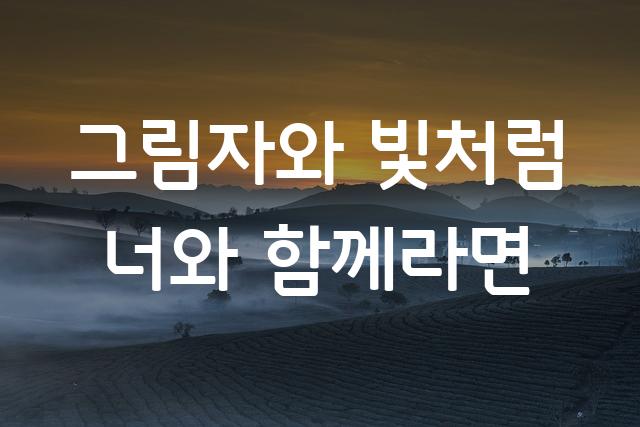
godo rounded는 NHN Commerce에서 제작한 폰트로, 그 이름처럼 동글동글한 영문 글꼴 특징을 가지고 있습니다. 이 폰트는 부드러운 곡선과 함께 친근하고 따뜻한 느낌을 전달합니다.
godo rounded은(는)
둥근 스타일, 감성적인, 자연감성, 부드러움, 복실복실 계열의 생김새를 가지고 있으며
로고 디자인, 광고 캠페인, 브랜딩 등에서 자주 활용되며, 효과적인 메시지 전달에 적합합니다.
이 폰트는 크리에이티브, 패션/뷰티, 건축/인테리어 분야에 잘 어울리며,
세련된, 창의적인, 고급스러운 느낌을 담고 있는 것이 특징입니다.